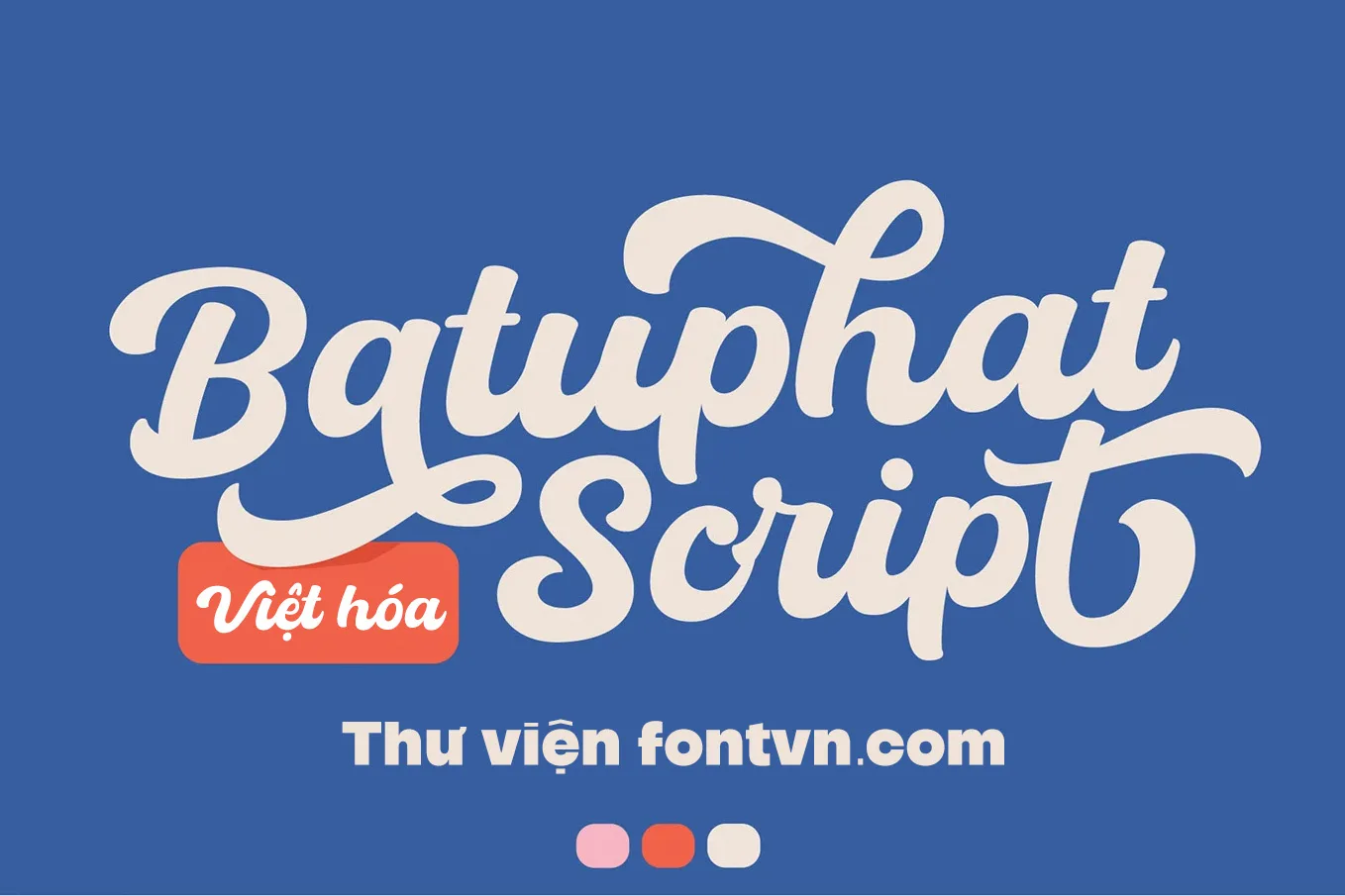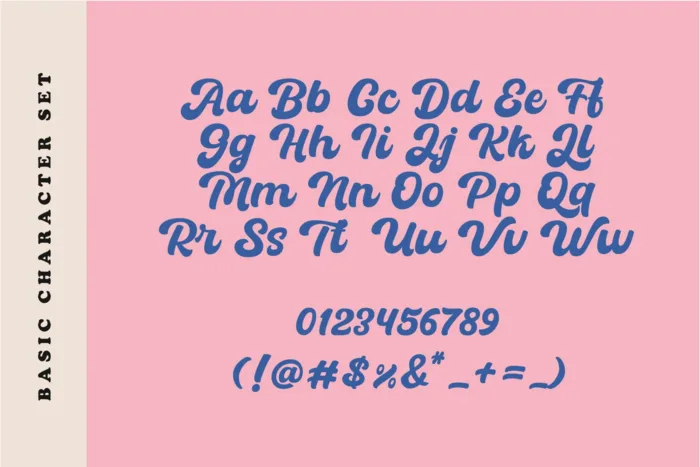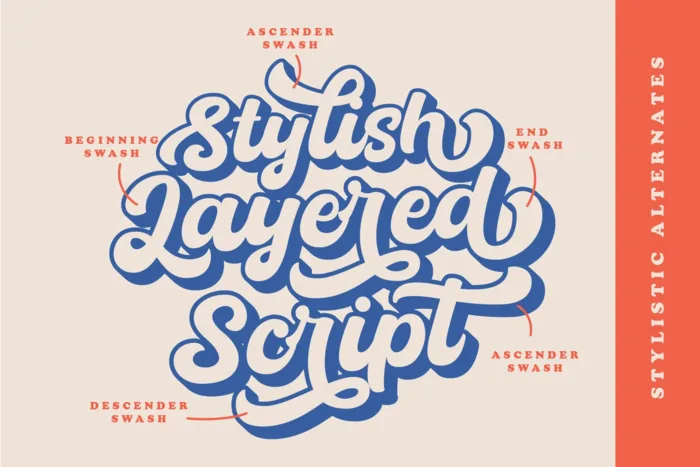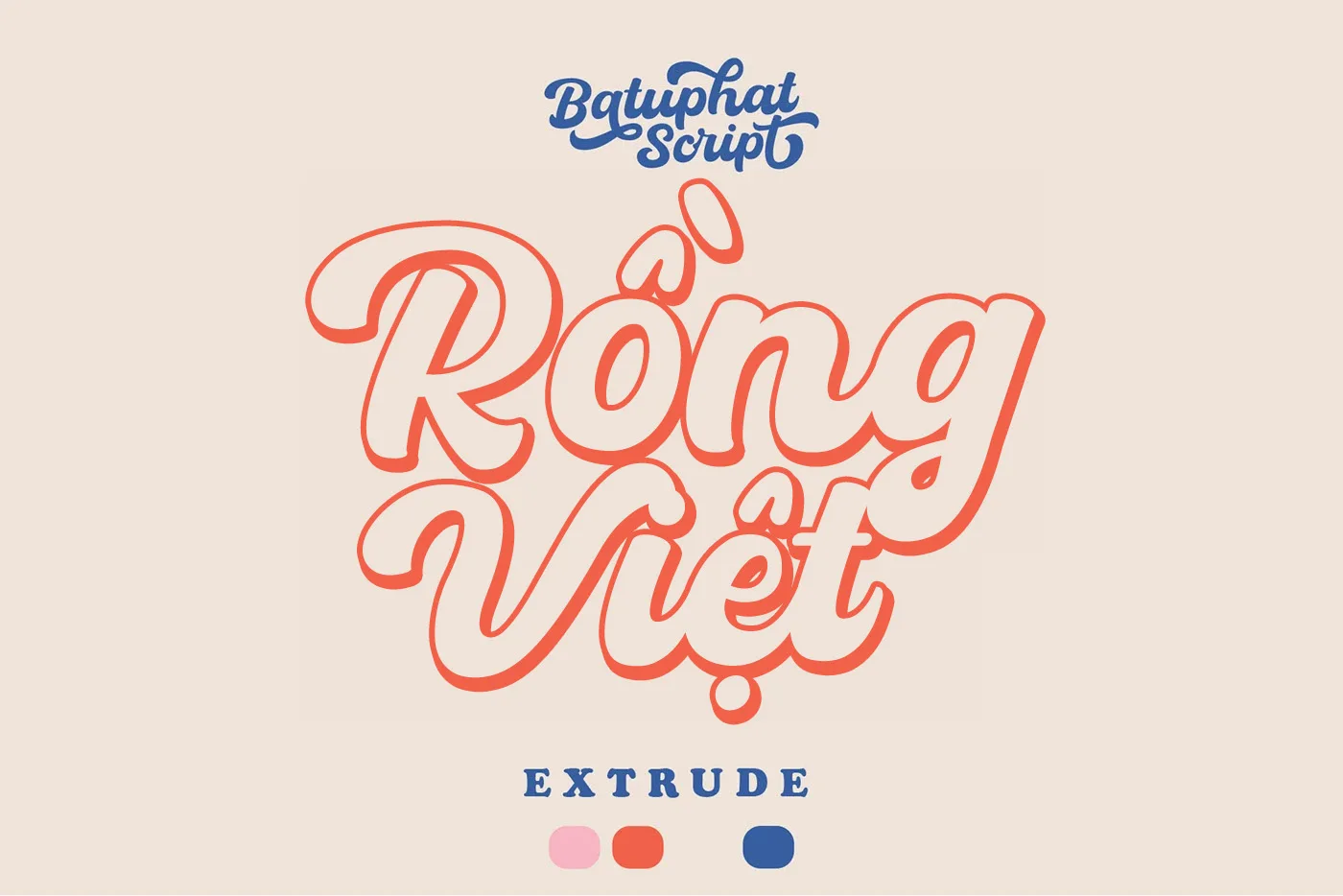
DVN Batuphat Script Việt hóa – Font script Layered hiện đại & phong cách
DVN Batuphat Script Việt hóa là một font chữ script mang phong cách hand lettering hiện đại, được thiết kế với dạng layered giúp dễ dàng phối màu và tạo hiệu ứng nổi bật. Font có đường nét mềm mại, uyển chuyển, phù hợp với các thiết kế mang tính thủ công, sáng tạo như logo, bao bì, signage, poster hay các dự án branding cá tính.
Bộ font bao gồm đầy đủ bảng chữ cái Latin, số, ký tự đặc biệt, hỗ trợ tiếng Việt có dấu, cùng nhiều swash & stylistic alternates giúp người thiết kế dễ dàng tùy biến chữ theo phong cách riêng. Đây là lựa chọn lý tưởng nếu bạn muốn thiết kế có chất “vẽ tay” nhưng vẫn giữ được sự hiện đại và chuyên nghiệp.